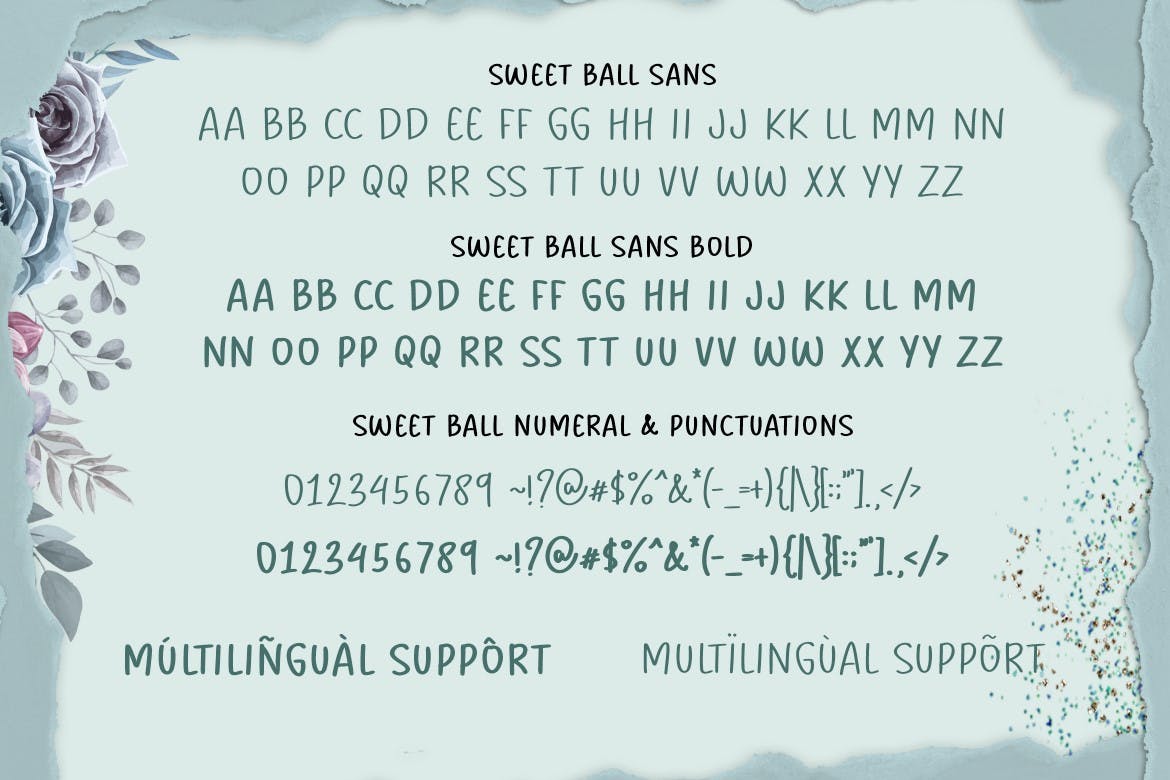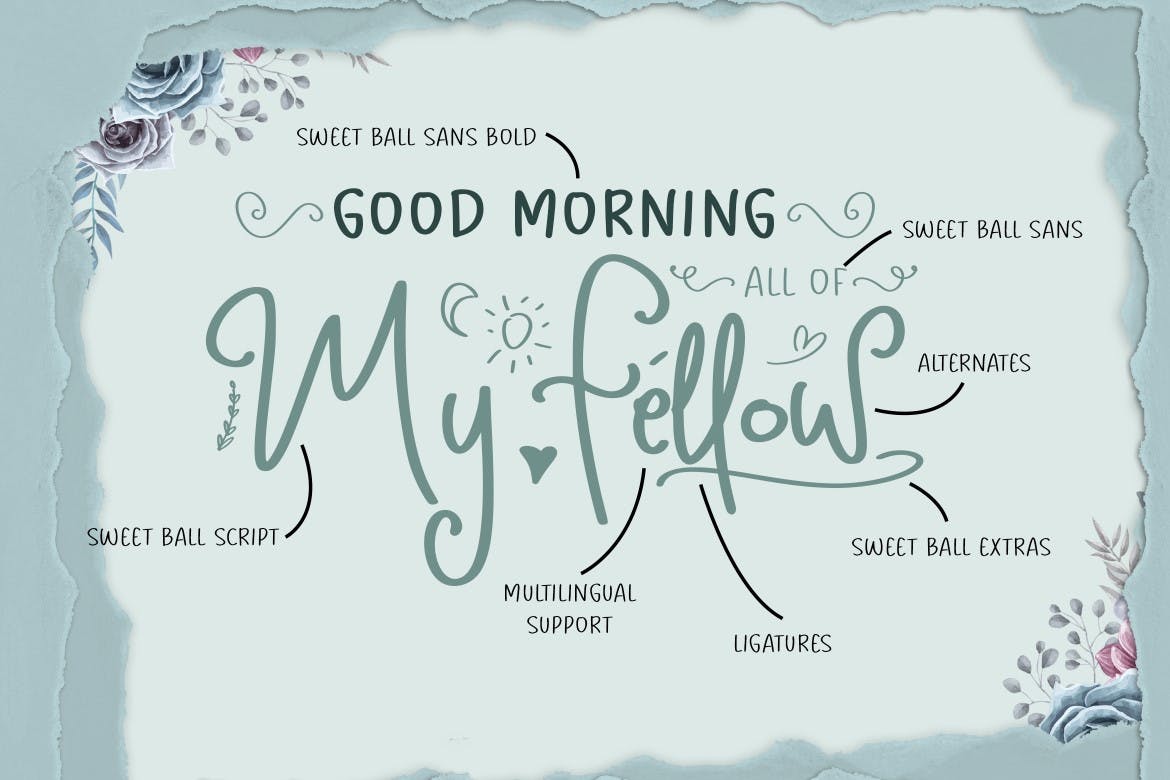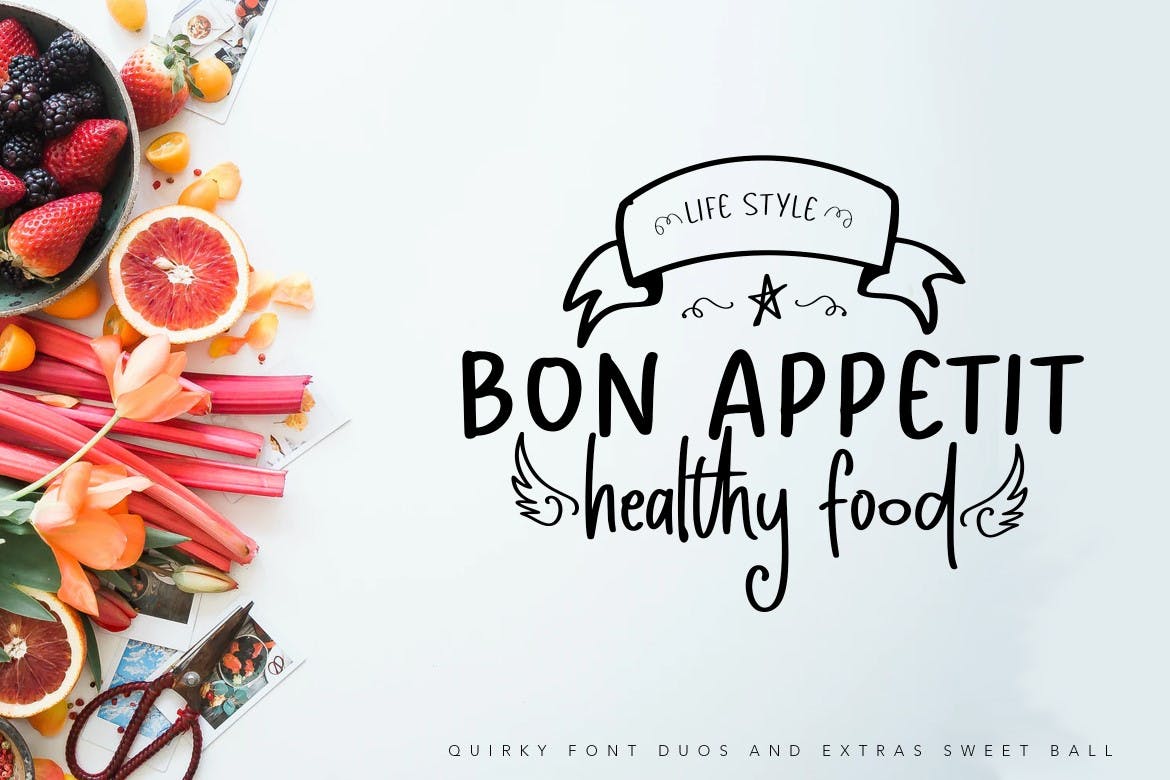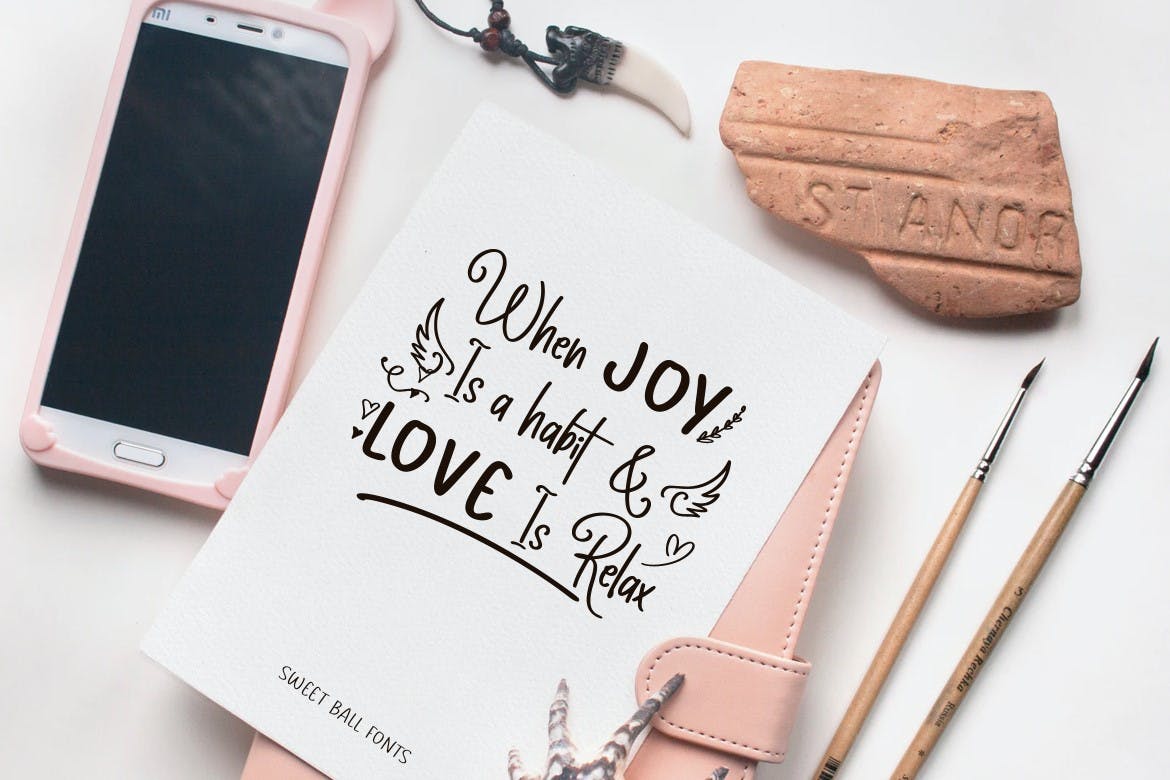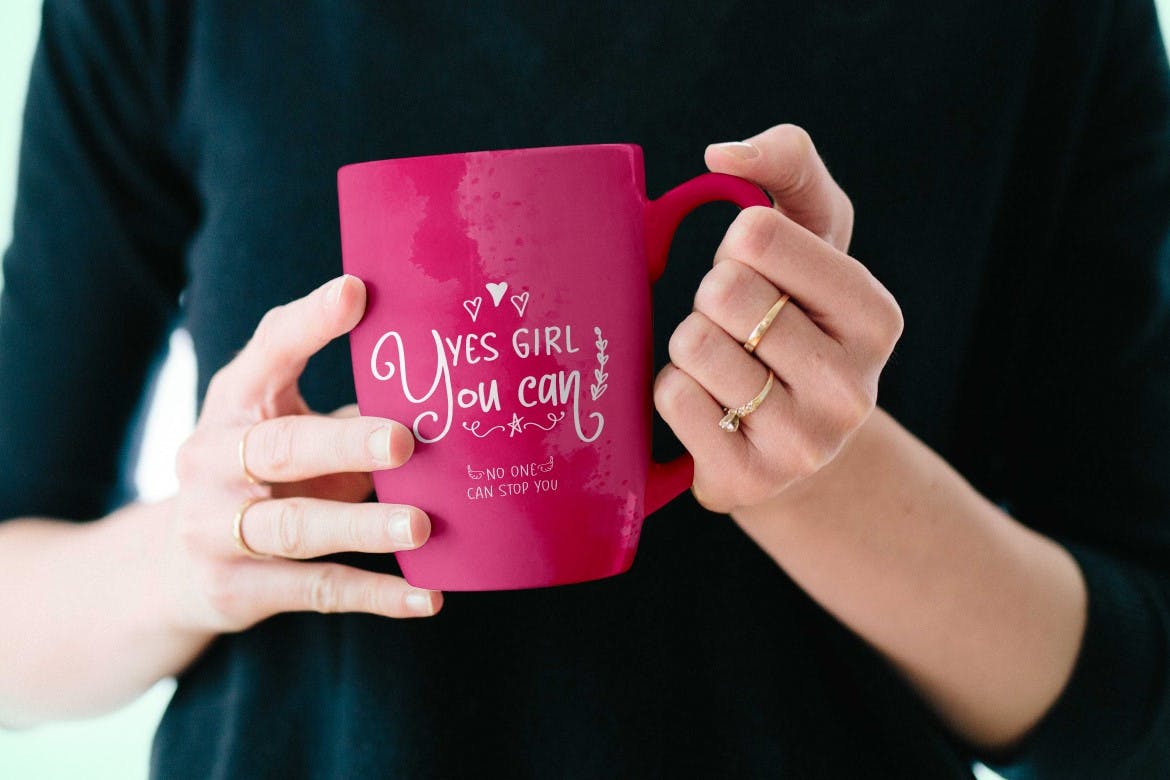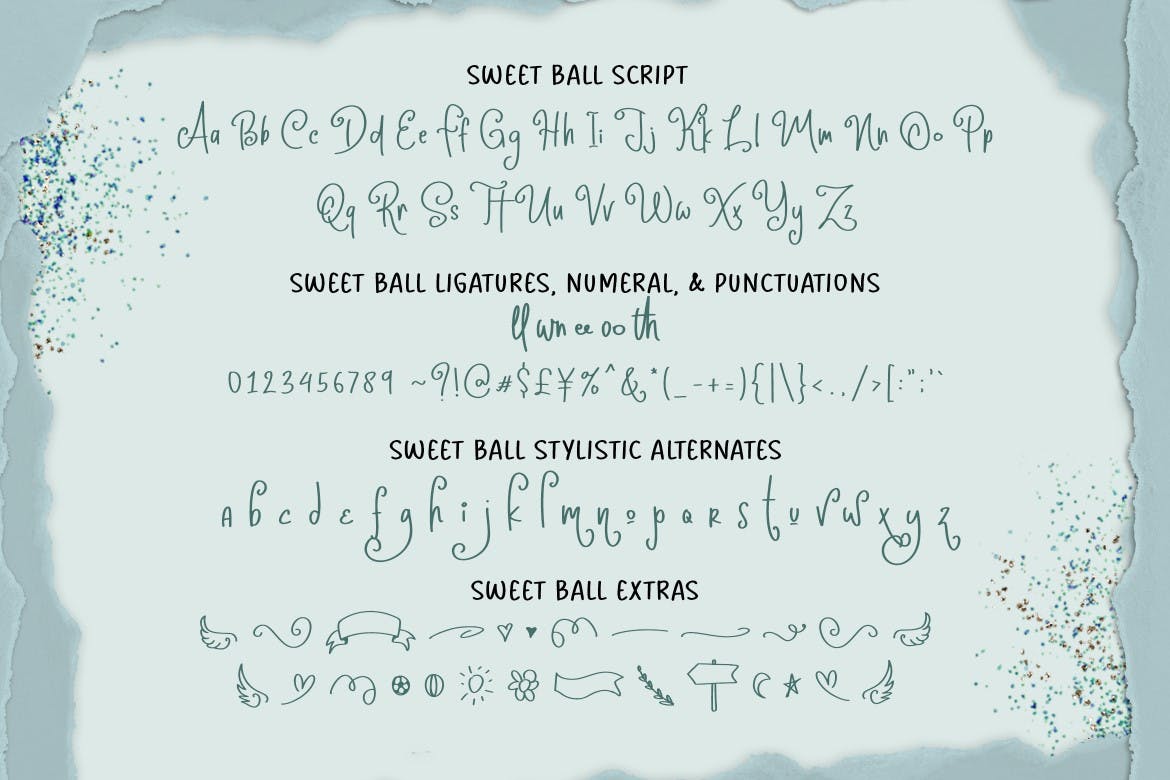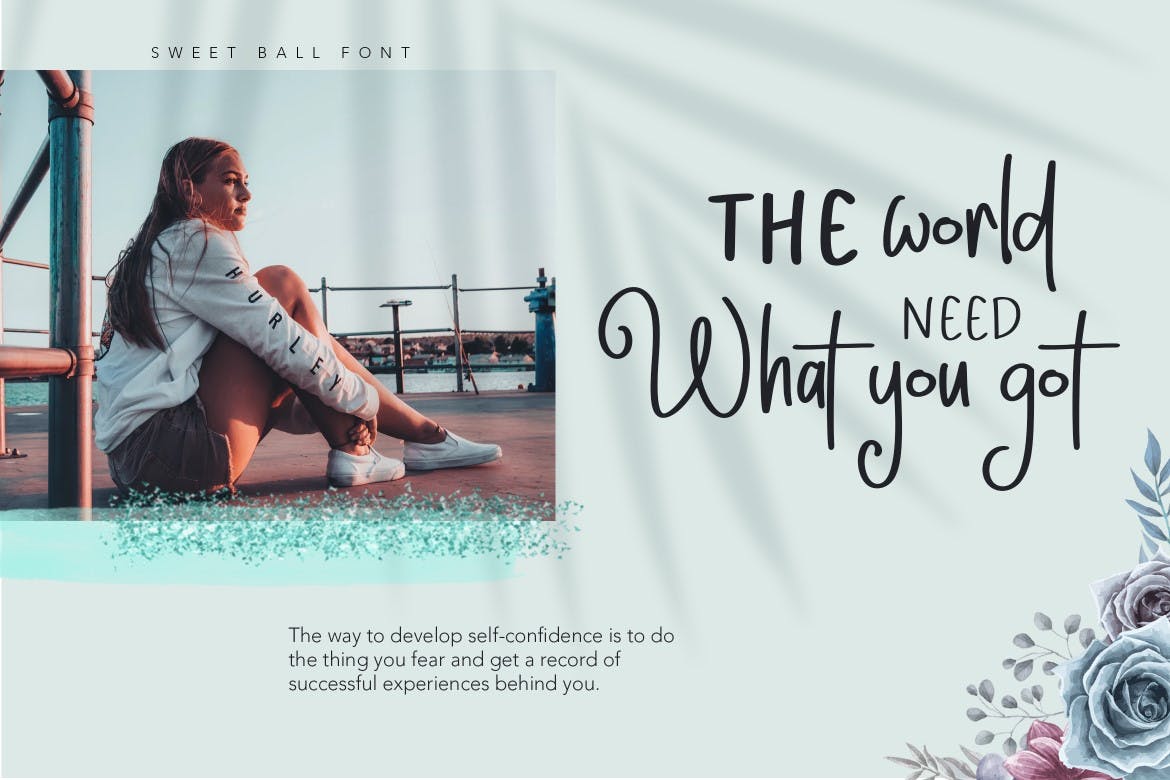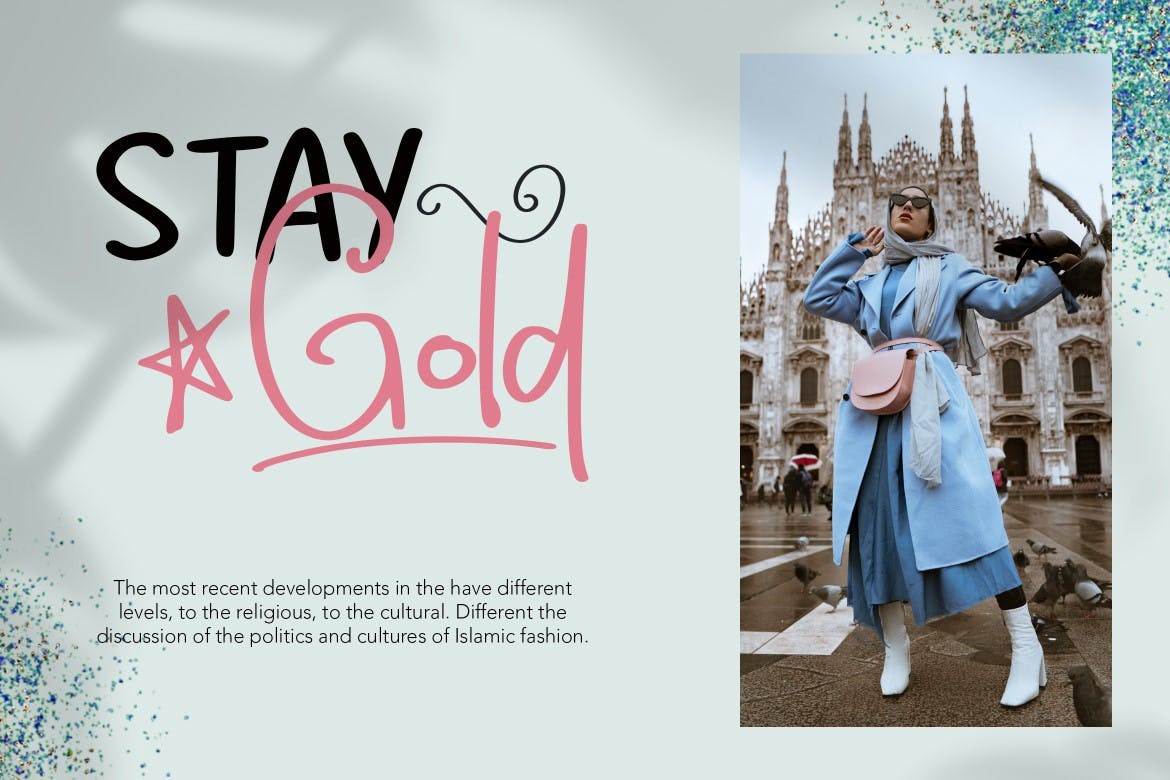
فونت Sweetball یک فونت جذاب و خطی با فضایی معاصر و فرم بینظیر است. این فونت که الهامگرفته از خوشنویسی مدرن و جاودانه است، بهگونهای طراحی شده تا زیبایی پروژههای شما را بهویژه در پروژههای دستی افزایش دهد.
مناسب برای طراحیهای هنری و دستی
قابل استفاده در پروژههای گرافیکی و چاپی
ایدهآل برای کارتهای دعوت، لوگوها و طراحیهای خاص